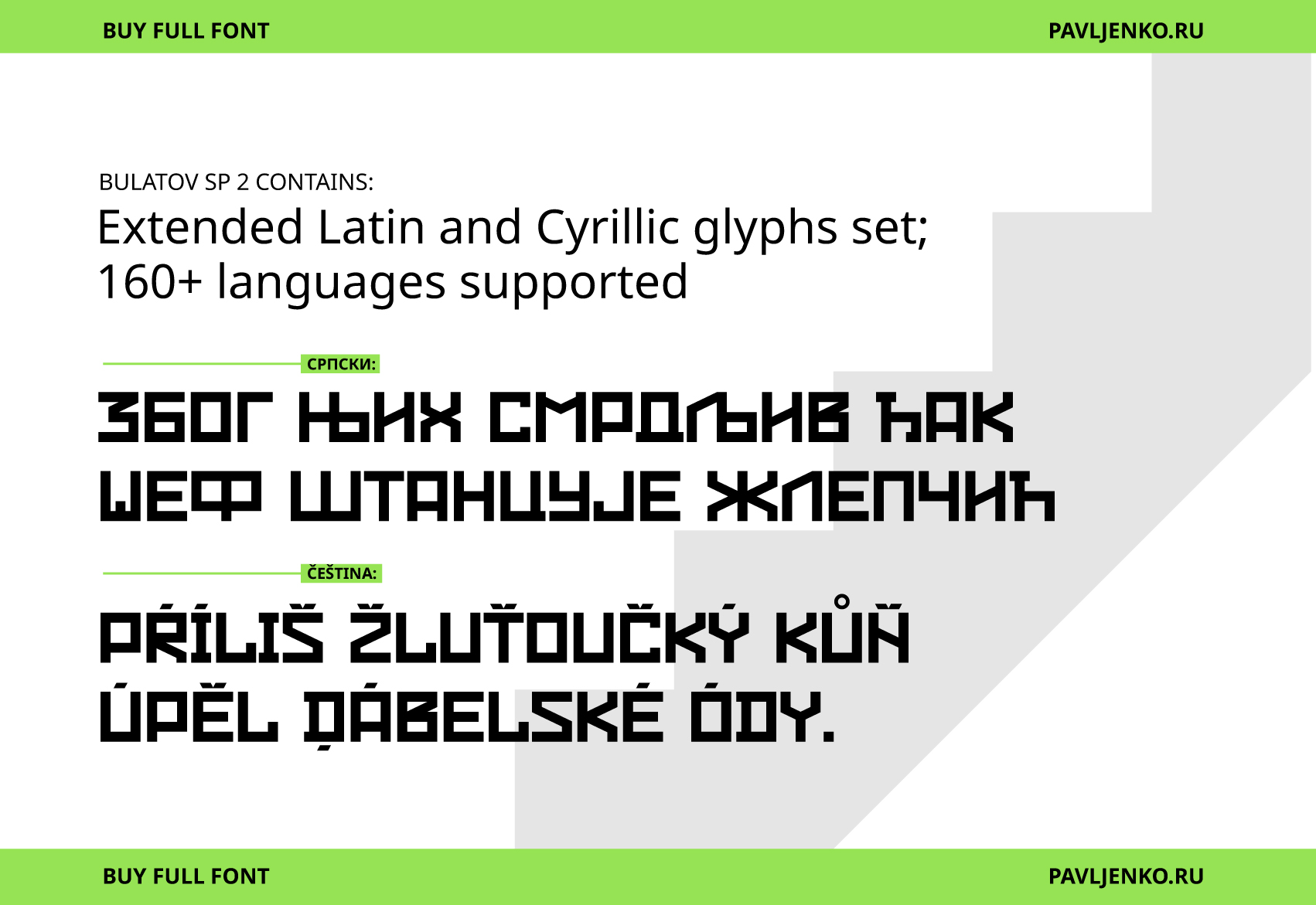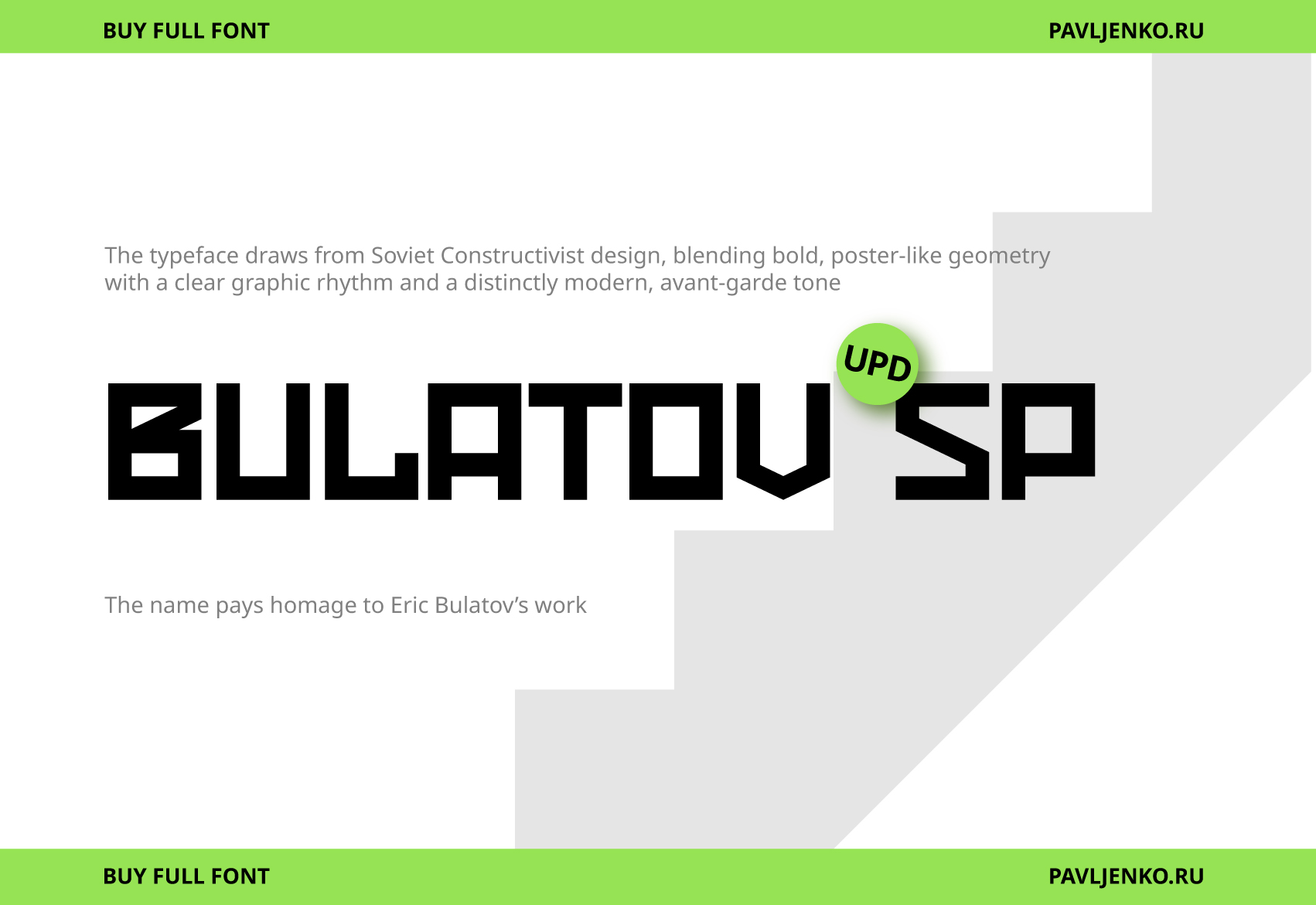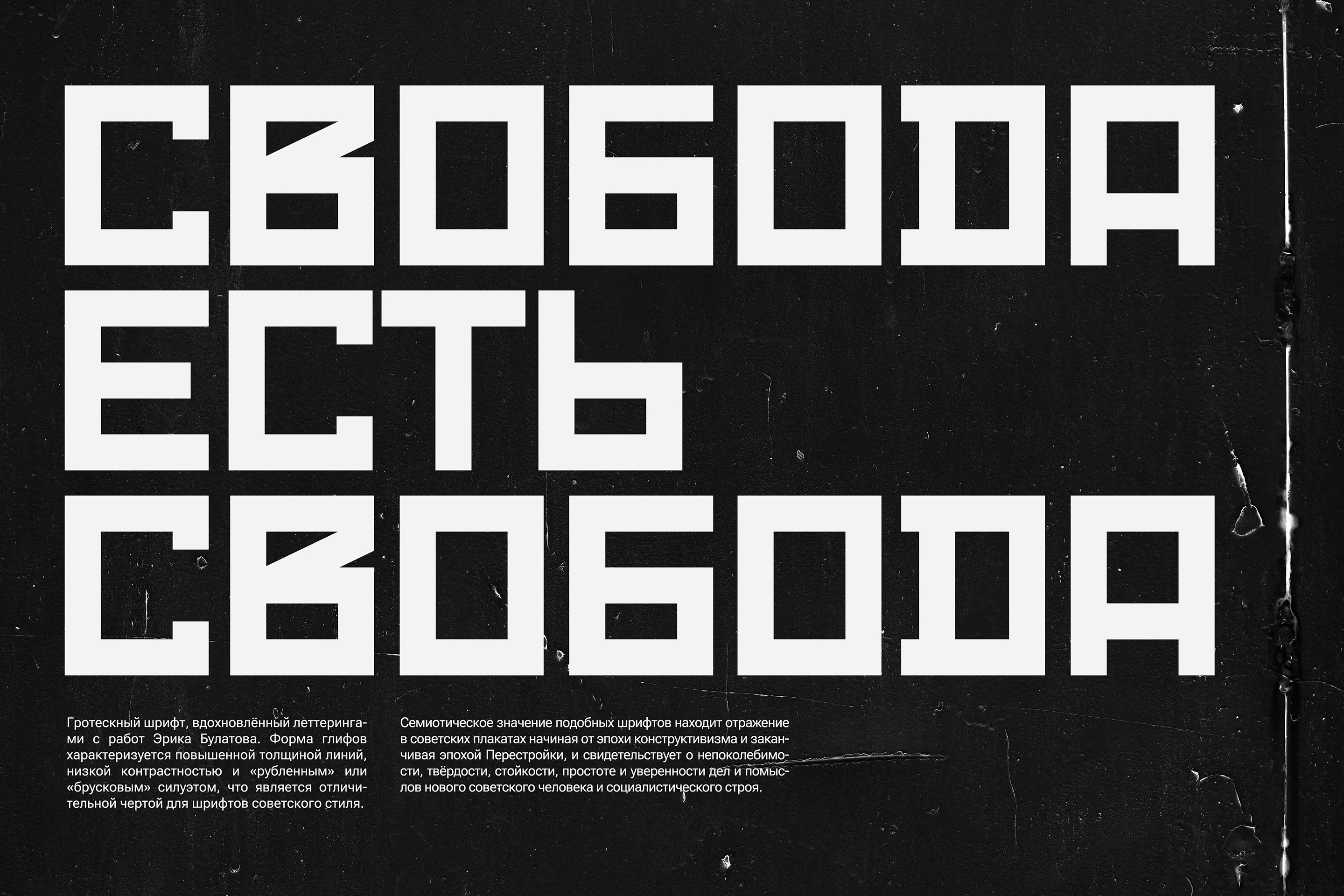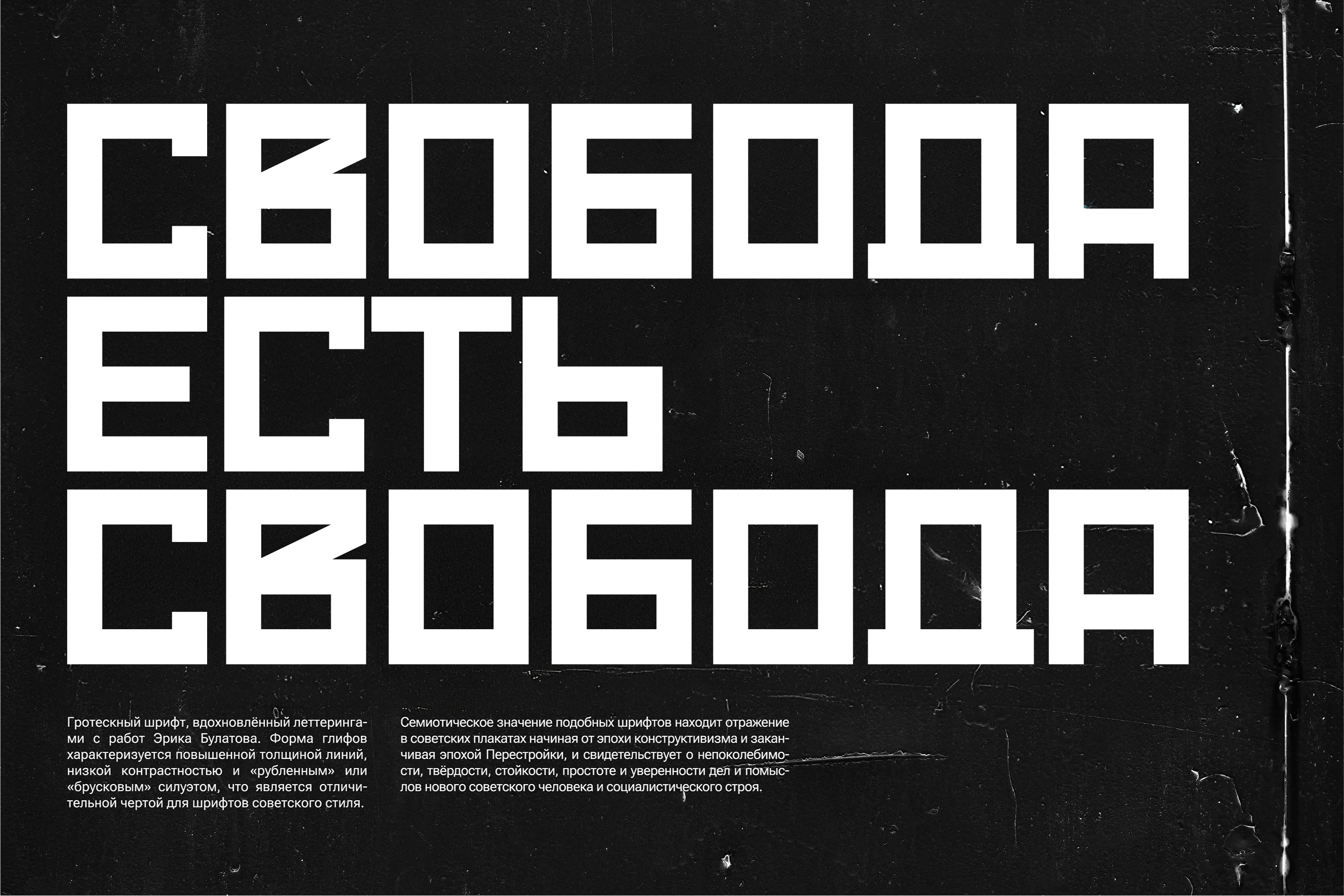
Шрифт Булатов
Bulatov — акцидентный шрифт, отрисованный по мотивам конструктивистской типографики двадцатых годов и вдохновлённый работами Эрика Булатова. Рисунок предельно графичен: строгие линии, выверенные толщины и наклоны, буквы посажены на жёсткую сетку и собираются в плотный ритмичный блок. Такая графика ложится в выставочные и брендовые макеты, обложки и титры — всё, где нужна геометрическая дисциплина. В комплекте — полная версия STAR и лицензия.
Designer Sasha Pavljenko